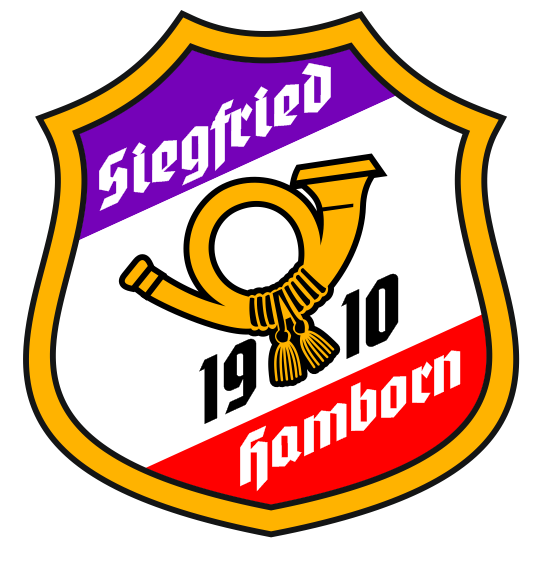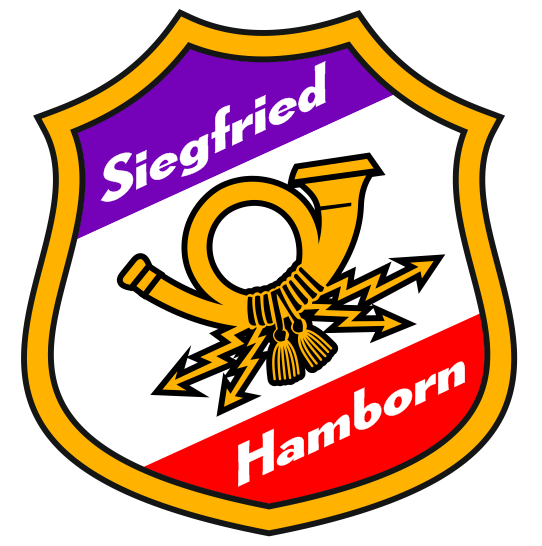
Wappen von Post Siegfried Hamborn
Schön und gut, aber bei Sportvereinslogos ist das nun mal anders. Meist ist Text drauf; ohne zumindest einzelne Buchstaben oder Zahlen geht es fast nie. (Von den großen deutschen Fußballvereinen fällt mir spontan nur der HSV ein.) Von daher sind Ratschläge zur Textlosigkeit nicht besonders zielgruppengerecht.
Wobei weniger Text sicher ein guter Rat ist. Sportverein und e.V. könnten sicher unter den Tisch fallen, ohne dass sie jemand vermisste. Dass ein Verein 1910 gegründet wurde, ist jetzt auch nicht sooo ungewöhnlich, dass man sich ständig damit brüsten muss. Solange es in Hamborn keinen anderen Postsportverein anderen Gründungsdatums gibt (und man 1910 als braucht, um die auseinander zu halten), würde ich es im Logo weglassen. Mit etwas mehr Mut könnte man sogar überlegen, Post wegzulassen, da dieses Erbe ja klar durch das Posthorn kommuniziert wird.
Sollte ich das Wappen renovieren, würde ich also zuerst eine Version nur mit Siegfried Hamborn anbieten. Löste das Proteste aus, noch eine Alternativversion mit Post Siegfried Hamborn.
Die Schrift wirkt – verzeih mir – etwas altmodisch. Entweder, das Logo braucht eine pure klare Serifenlose oder etwas, das die Tradition betont – mit amtlichen Serifen!  :nicken:
:nana: Und übrigens: Pauli würde Euch ganz schön was husten, wenn Ihr denen die 1910 wegrationalisieren würdet. Die gehört zum Markenkern! Ein Sportverein, der 1910 gegründet wurde, ist schließlich schon über 100 Jahre alt, das ist doch schon was!
Warum hat das Posthorn übrigens diese Blitze, die waren doch im Original nicht drin?
Doch. Bis ’79 in dieser Form, danach noch stilisiert. Man hat ja nicht nur Briefe ausgetragen, sondern auch Telegramme und gesprochene Nachrichten, sog. Telephonate, transportiert. Über Drähte! Mit Elektrizität!
Ja, aber ich meinte mit Original doch das Posthorn im Sportwappenlogo. Da waren doch keine Blitze drin.
Ja, nee, aber das war ja hier im Strang schon festgestellt worden, daß das so, wie es war, sowieso überhaupt nicht geht und durch ein Horn mit besserem Klang ersetzt werden muß.
Die Schrift wirkt – verzeih mir – etwas altmodisch.
Die Schrift ist nicht ideal, aber ich denke, Catfonts wollte nur kurz zeigen, wie aufgeräumt eine vereinfachte Struktur wirken kann und hat die nur als Platzhalter reingebaut.
Die 1910 würde ich auch drinlassen, die kann man recht schmerzfrei mit unterbringen, ohne daß das gleich wieder überladen wirkt und für den Identifikationswert des Vereins ist sie sicherlich unverzichtbar.
Die Schrift ist nicht ideal, aber ich denke, Catfonts wollte nur kurz zeigen, wie aufgeräumt eine vereinfachte Struktur wirken kann und hat die nur als Platzhalter reingebaut.
Ja, vermutlich!  :nicken:
um da schnell Beispiele zeigen zu können, hatte ich einfach auf ein Posthorn aus meinem Fundus zurückgegriffen. Das kann  man natürlich entblitzen , nur die Arbeit wollte ich mir für ein schnelles Beispiel nicht machen. aber gut, entblitzt...
Und mit der Schrift, ja stimmt, ohne große Auswahl ein schneller Platzhalter, da könnte man sich dann noch Gedanken drüber machen. Ich kann jedoch noch altmodischer :-)
19 Hornquaste 10 gefällt mir gut. Da stört die Jahreszahl kein bisschen und die Traditionalisten (ich verbeuge mich demütigst gen Hamburg :bow:) sind bedient.
Und – nur damit niemand auf die Idee kommt, die doch zu nehmen – solch eine schlichte Gotisch geht nun gar nicht. Entweder eine schlichte (auf den ersten Blick zeitlose; ich wäre für eine serifenlose) oder, wenn es unbedingt historisierend sein muss, eine, die auch 1910 hätte verwendet werden können. Aber eine, die untrennbar mit den 30er Jahren ± ein paar Jahre verbunden ist, nee. Für einen bewussten zeitlichen Kontrast ist sie da einfach zu nah dran.
Ohne Schwarz gefällt es mir übrigens deutlich besser (so wie der Catman™ das weiter oben schon mal gezeigt hatte). Das wirkt luftiger und zeitgemäßer.
Und – nur damit niemand auf die Idee kommt, die doch zu nehmen – solch eine schlichte Gotisch geht nun gar nicht.
Du kannst sagen, was Du willst — im Vergleich zu den anderen 3 Alternativen (Grotesk, Fraktur, Schreibschrift), ist die von der optischen Wirkung her mit großem Abstand die beste. Flächig, klar, lesbar, plakativ. Sie leidet in ihrer Robustheit auch am wenigsten unter der Idee, die Schrift gegen die Wappenebene zu kippen (so ganz unbeschadet übersteht sie es aber auch nicht). Es wären jedenfalls keine graphischen Gründe, warum das »nun gar nicht geht«, sondern nur die umstrittene Ideologieverhaftung und vielleicht die Erwägung, daß die Schlichte Gotisch 1910 eben noch nicht verbreitet war. Aber vielleicht findet sich ja noch eine schmalfette Grotesk mit ähnlicher Wirkung. Oder etwas in die Richtung:
zeugt das meiner Meinung nach von etwas magerem Selbstbewustsein, denn dierses scghnell dahingeworfene soll ja gerade den Raum für eine ordentliche, seine Zeit und Erfahrung benötigende Ausarbeitung sein. Und letztlich tur jeder gut daran, zwar Ideen zusammen zu tragen, die endgültige Form dann aber von einer/m Fach-Frau/Mann machen zu lassen.